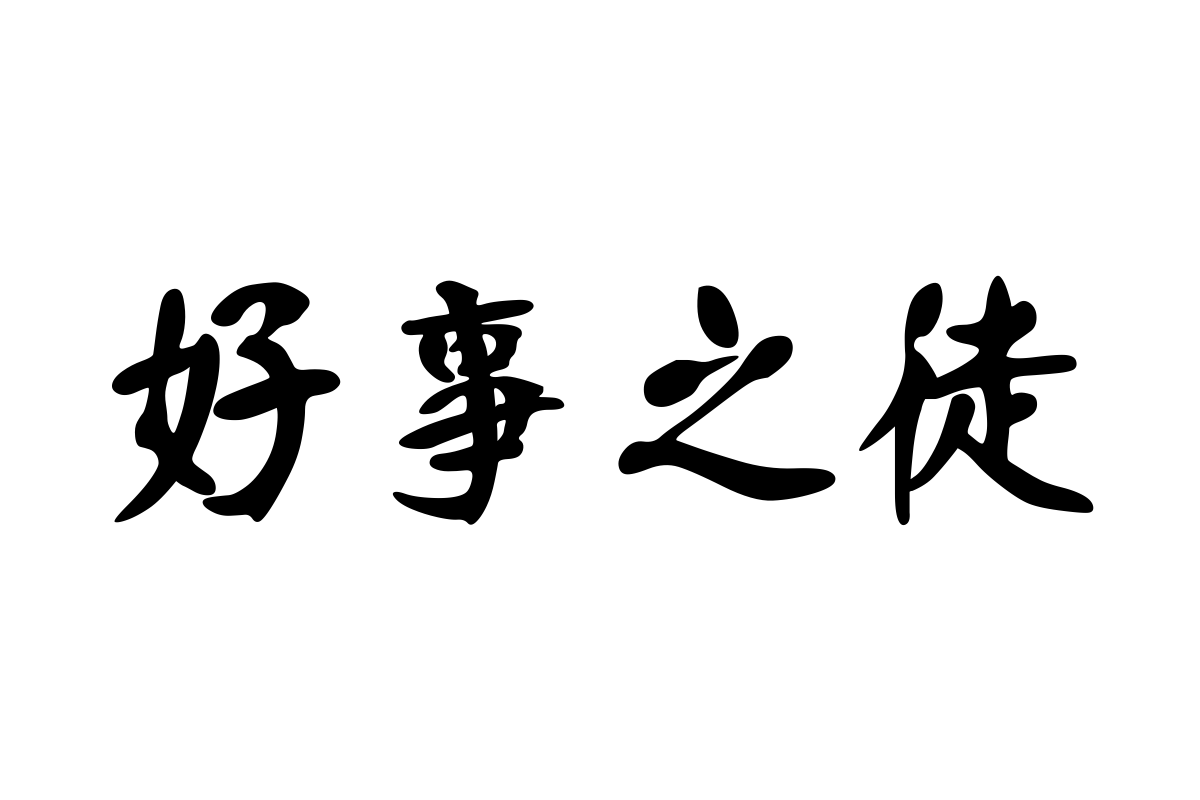
汉标精工粗犷体是一款具有独特风格和特色的中文字体,它采用了粗犷的设计风格,给人一种强烈的视觉冲击感。这款字体笔画粗壮有力,结构紧凑,线条流畅自然,既有传统的韵味又不失现代感。它的字形结构独特,既有传统的楷书、行书的特点,又有现代的简约风格。这种独特的设计使得汉标精工粗犷体在众多字体中脱颖而出,成为了一种独具特色的字体。
该字体适用于各种需要强调力量和动感的设计场景,如广告、标志、包装设计等。它能够很好地传达出产品或品牌的独特个性和精神内涵,增强视觉效果。同时,汉标精工粗犷体也适合用于一些需要表现粗犷、豪迈风格的文学作品,如诗歌、散文等。
总的来说,汉标精工粗犷体是一款非常独特且实用的中文字体,无论是在商业还是艺术领域都能发挥出巨大的作用。